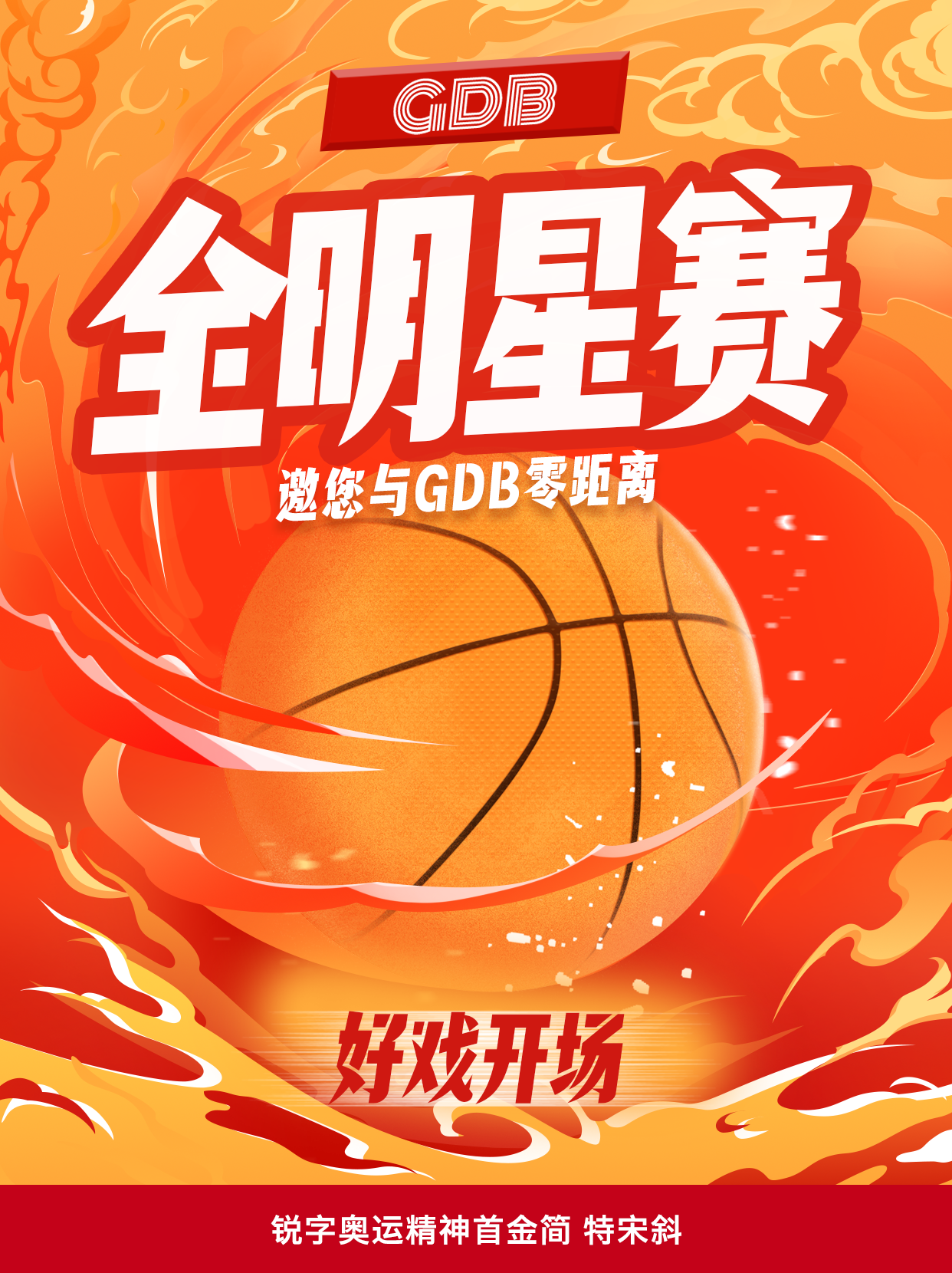
锐字奥运精神首金简 特宋斜
REEJI-ShoujinGBItalic Black
该字体是一款非“典型”宋体字,它字型瘦长,中宫适中,并简化了部分宋体的装饰角,字体整体倾斜8度,呈现出一种更加简约、更具现代感的质感。最具特色的是锋利的斜笔画与干净利落的笔画切割,轻盈而又坚毅,寓示运动员们夺金历程的美好的开始。